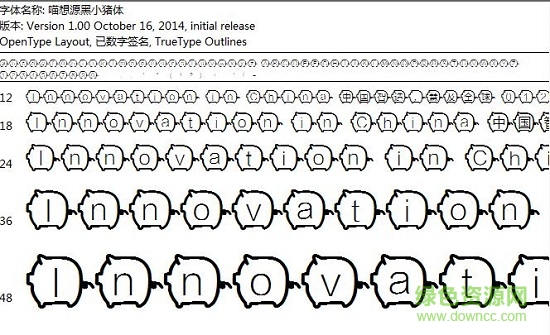
小豬體ttf是一款非常女性化的字體,這款字體會(huì)讓你的電腦輕松的變得可愛起來,有喜歡這款字體的朋友可以來綠色資源網(wǎng)下載使用!
小豬體ttf是一款非??蓯鄣?a href="http://m.lz0519.com/k/yishuziti/" target="_blank">藝術(shù)字體,這款字體最大的特色就是每個(gè)字都被一只可愛的小豬包圍著,非常的q萌,適合用來進(jìn)行當(dāng)做主題或者是聊天字體!